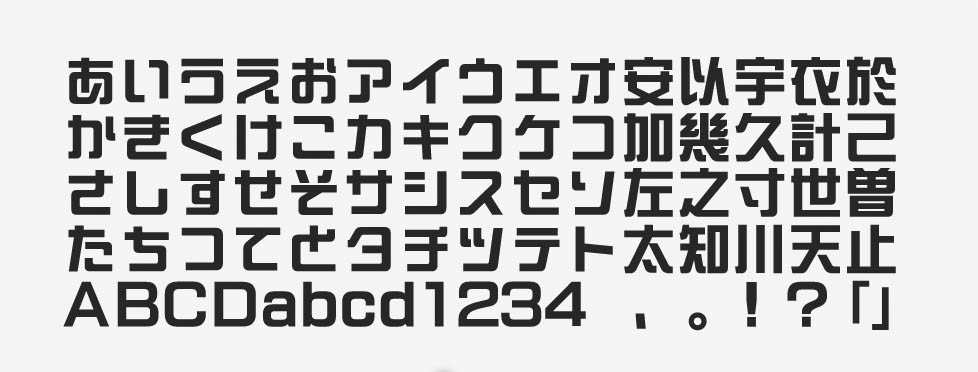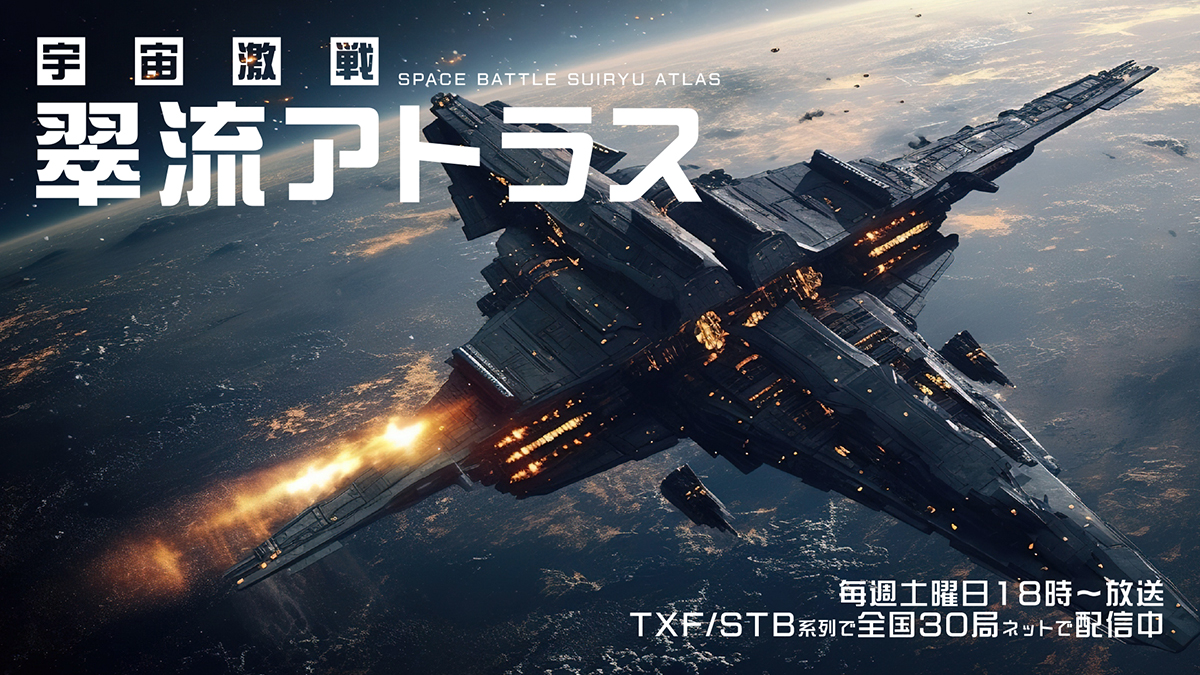
「翠流アトラス」について
2022年から展開されている「翠流シリーズ」のラインナップの1つです。同シリーズのフォントは、Arphic Types のAR新藝体の漢字に、モリサワで制作したひらがなや英数字を組み合わせて構成されています。
「翠流アトラス」の特徴
翠流アトラスの文字は四角ばった幾何学的な形で、水平・垂直を強く意識しながらデザインされています。ロゴに使いやすく、アニメやゲームでの近未来的な雰囲気にもぴったりです。字面が大きくて、見る人に強いインパクトを与えます。
スクエアな骨格のフォントですが、必要以上に堅すぎる印象はありません。そのポイントは、一部の漢字のエレメントや平仮名の四隅に取り入れられた角丸の処理です。クールな表情と馴染みやすさが両立されています。
翠流アトラスは、今回の作例のように主に大きめのサイズで短めのテキストを組むのに適しています。動画配信のテロップやタイトル表示などでも良い視覚的効果が表現できるでしょう。角丸加工してみたり、縦横比を変形させたりと、かなり加工し甲斐もあるフォントだと思います。